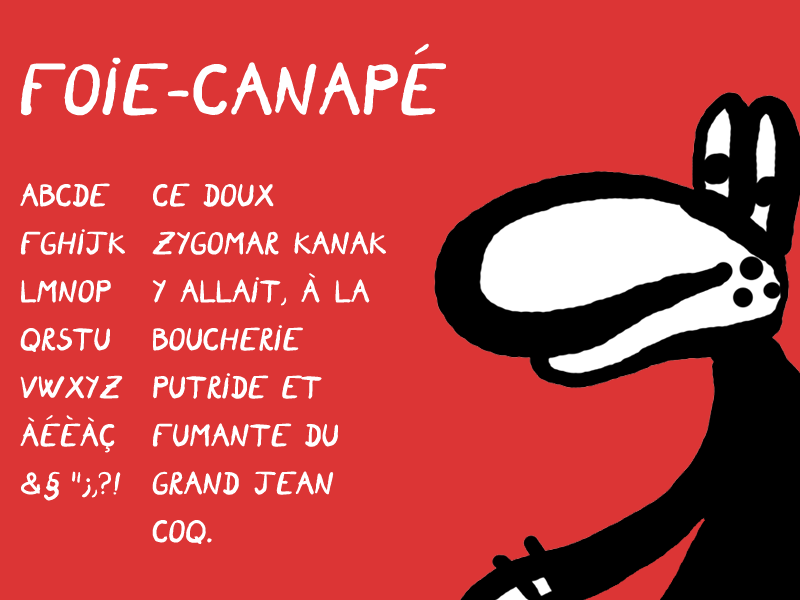
Шрифт Foie Canape
Voici la version complète et gratuite de cette police de caractère, "Foie Canapé".
Elle est dessinée à la base pour le lettrage en Bande Dessinée.